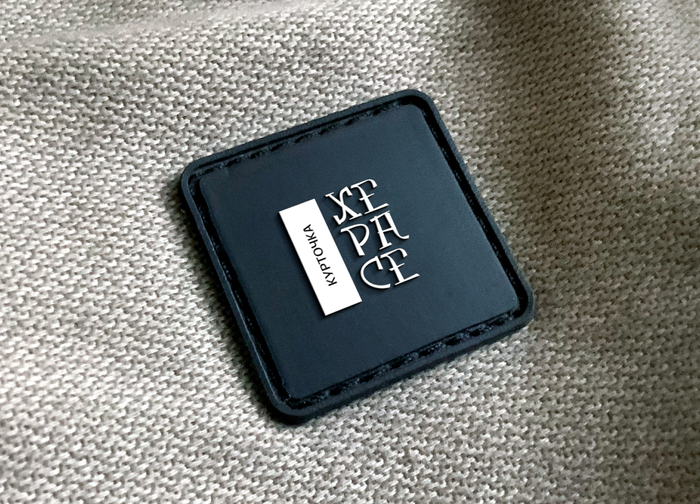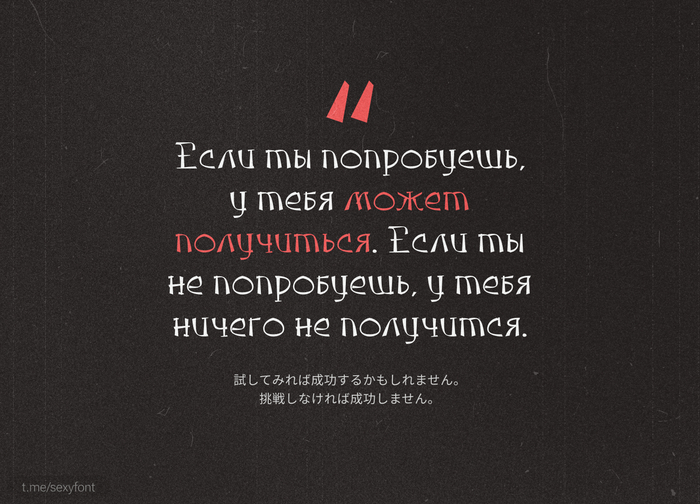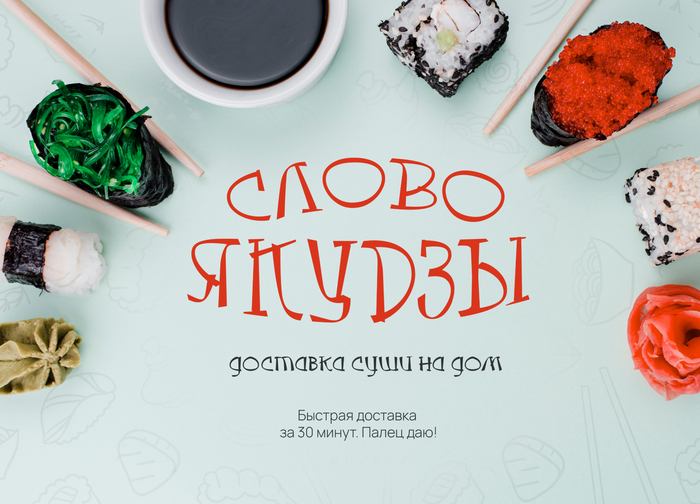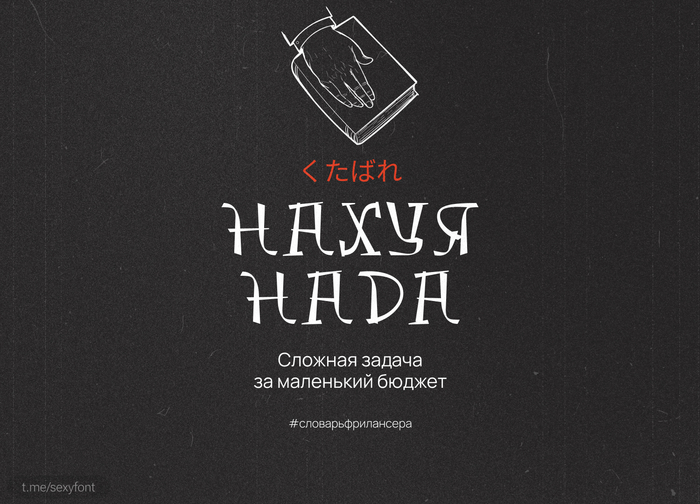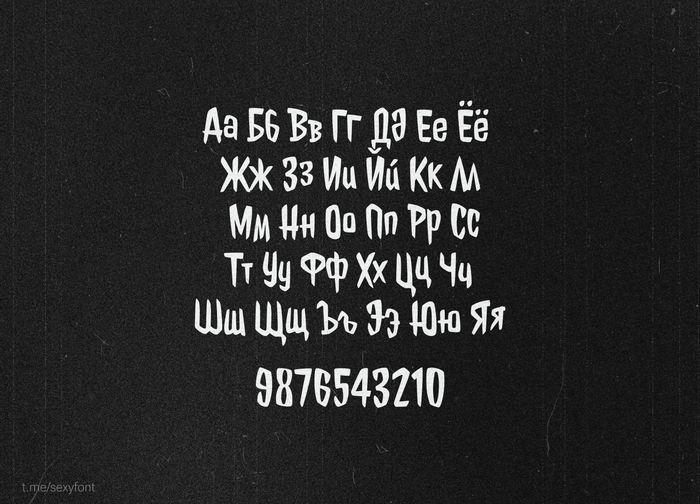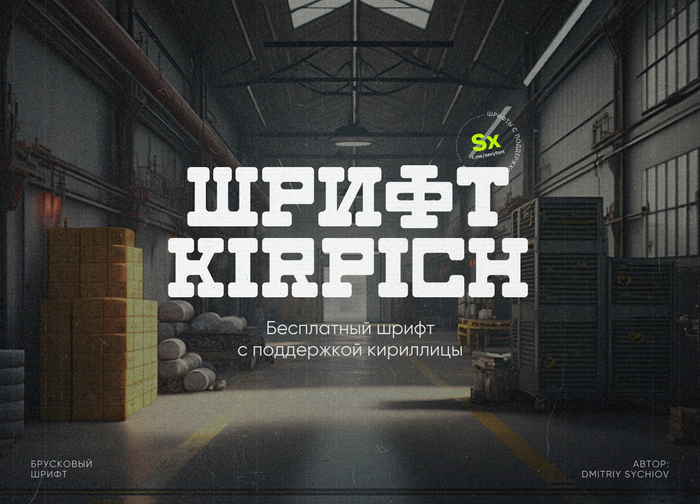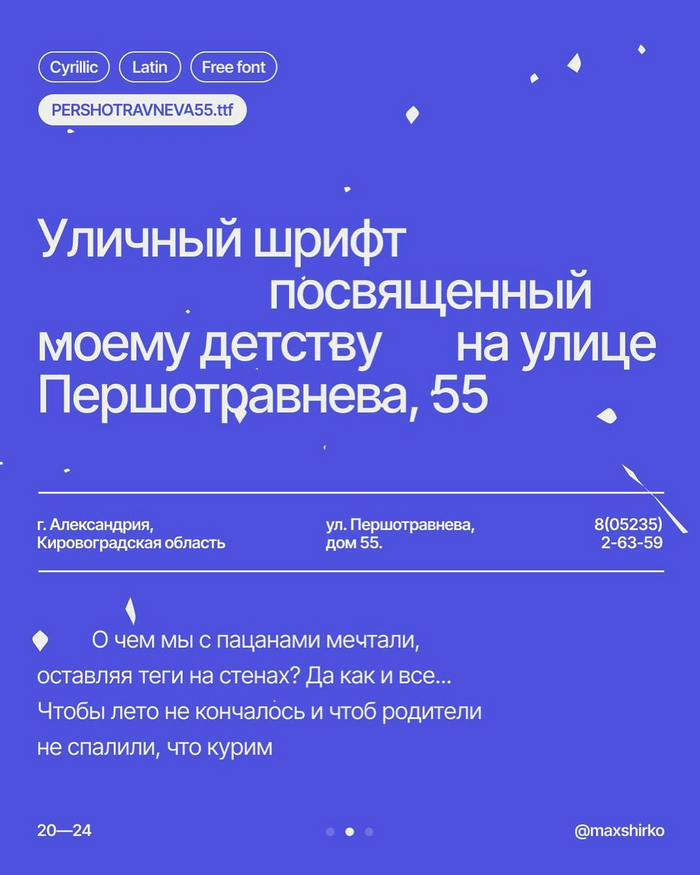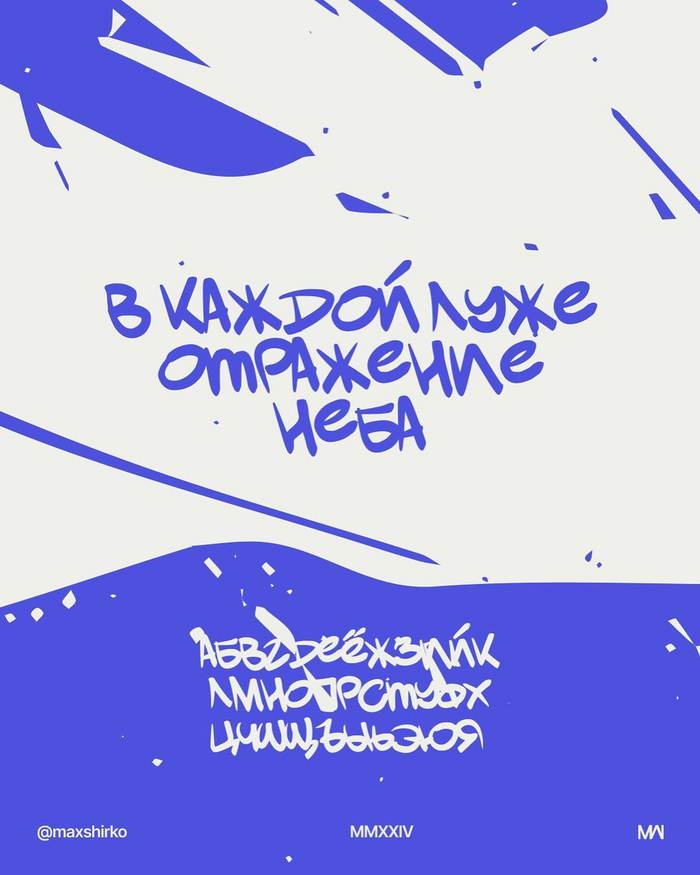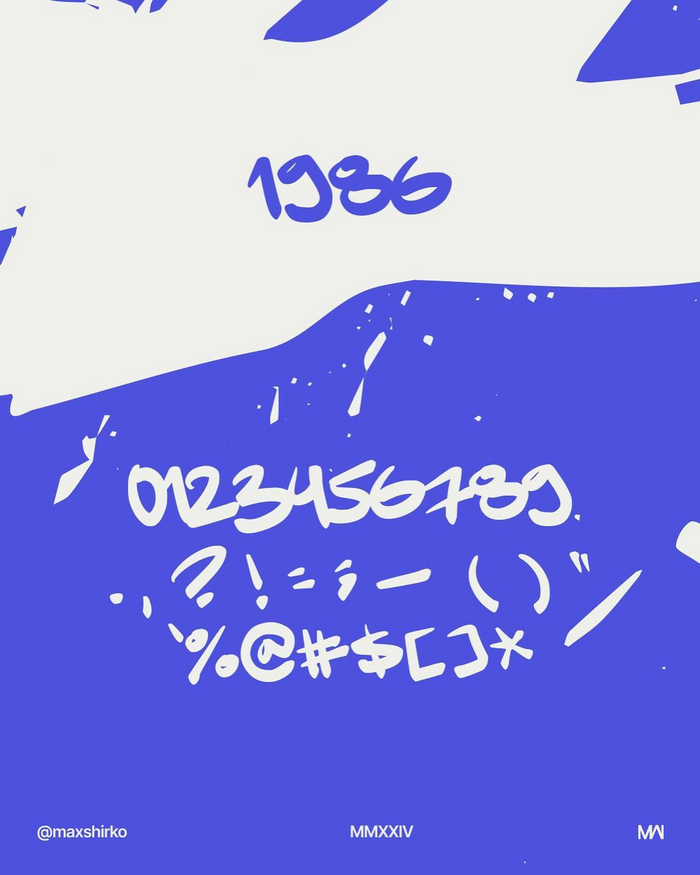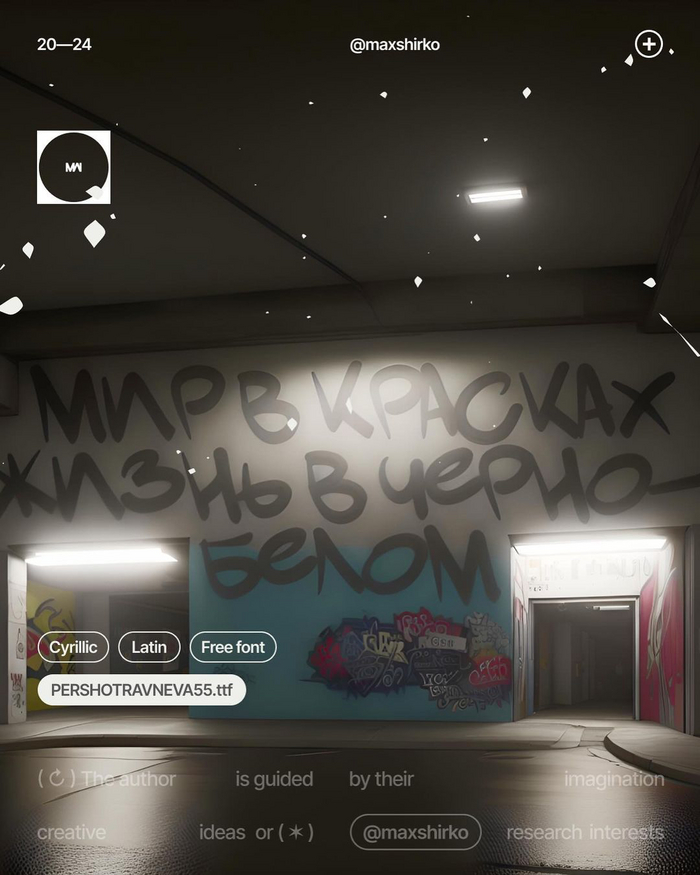
Шрифт Медведь
Дмитрий Тектов радует нас новым декоративным шрифтом в уже узнаваемом стиле. Бесплатно для любого вида использования. Автор: Дмитрий Тектов
От автора: Сделал шрифт для себя, но дарю его всем и каждому.
Это что-то из обрывков воспоминаний о тегах на стенах, о исписанных полях в тетрадках, любимых маркерах и несбывшихся мечтах рисовать стритарт. Акцентный, наглый, бунтарский и наивный шрифт Pervomayskaya55
Лови Kirpich. Плотный и игривый шрифт в слегка западном стиле.
Рисованный шрифт в виде детских каракуль. Отлично подойдет для добавления поясняющих подписей или стишков)
Jolly Lodger. Весёлый шрифт с поддержкой кириллицы.Шрифт входит в коллекцию Google Font. Поддерживает латиницу и кириллицу.
Был вдохновлен уникальной японской каллиграфией и основан на японской концепции дизайна. Идеально подходит для создания творческих работ с японскими, азиатскими и восточными концепциями.
«Этот шрифт я сделал, как итоговый проект на курсе. С тех пор ничего в нём не менял. И только сейчас решил поделиться. Со всеми наивными ошибками и недоделками. Пусть будет! Итак, встречайте, Метрика!»